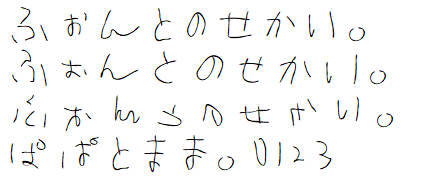
制作者:KrK (Knuth for Kludge)
Iwata Clip Studio Comic Regular
- ©イワタ
- 文字それぞれに4つの字形を収録
- 入力する度にランダム表示される
- それにより、手書きのような組版を実現
- 一人称の「I」に自動でセリフが付く機能を搭載
- 大文字のみなのが残念…
TA礼筆
- ©スキルインフォメーションズ
- かしこまった、綺麗な文字
ARペン行楷書体M
- ©Arphic Technology
- 行書と楷書の間?
- 画像は英文が『AR Pペン行楷書体M』
NSK P白洲ペン楷書
NSK P白洲ペン行草
DFPてがき速W3
- ©ダイナコムウェア
- 等幅版あり
- 英文表記の習慣が漢字にも色濃く表現された手書き風書体
- 活発で生き生きとしたリズム感のあるスタイルを存分に表現
塩化速記フォント
- ©松本
- 速記したような字体
- 第二水準+α
- 一部略字も使用
瀬戸フォント
- ©瀬戸のぞみ
- JIS第四水準まで
- 3万文字以上
- 読みやすさと親しみやすさのバランスが取れた手書き風フォント
妹フォント標準
- ©おてこ
- 拡張漢字までほぼ収録
- 妹が一生懸命、丁寧に書いた文字
左利きの彼女
- ©渋谷瞳
- 全第一水準+530字ほど+常用漢字+人名漢字
- 小学校3年生までに習う漢字のみの無償版あり
- 左利きの作者が丁寧に書いた手書き文字
- 手書きの味を出すため全ての文字を手書き
ことり文字ふぉんと
- ©Aya*
- 2weight
- 等幅版あり
- 書籍『もえたん』に使用された
ことり文字ふぉんとPro
- ©あや*
- 2weight
- 等幅版あり
- 上記から改訂が加えられている
kawaii手書き文字
- ©spicy-sweet
- 約2,300字の漢字(すべての教育漢字・常用漢字、一部の第一・ 第二水準)
- ちょっぴりクセのある可愛い手書きペン字をひとつひとつフォント化
- とぼけた雰囲気を生み出す手書き風フォントの草分け的存在
ねこふみフォント
- ©ネコフミワークス
- 第一水準+第二水準+拡張漢字+ごく一部の第三水準漢字
- 猫たちに紙を踏まれながら書いた手書きの日本語フォント
- 猫ファーストで書かれた、ゆるくてかわいい文字
またたびフォント
- ©ネコフミワークス
- 2weight
- 第一水準+第二水準+拡張漢字+ごく一部の第三水準漢字
- ほんとうに酔っぱらって書いた文字
- コンセプトは「猫にまたたび、かいぬしお酒」
ねこのけフォント 夏
- ©ネコフミワークス
- 2weight
- 第一水準+第二水準+拡張漢字+ごく一部の第三水準漢字
- スッキリとした細字手書きフォント
- 夏の暑さに備えた猫のスッキリした毛並みをイメージ
ねこのけフォント 冬
- ©ネコフミワークス
- 第一水準+よく使われる第二水準
- 丸文字の手書き日本語フォント
- 冬の寒さに備えて毛を蓄えた猫のふっくらふわふわな毛並みをイメージ
HolidayMDJP05(ホリデイ)
- ©Maniackers Design / Masayuki Sato + Hiroko Takiguchi
- 第一水準まで
- フツーにメモを書いたかのような自然な雰囲気のフォント
- 「元祖手書き文字フォント」とも言われる
エビハラのくせ字
- ©NaotoEbihara